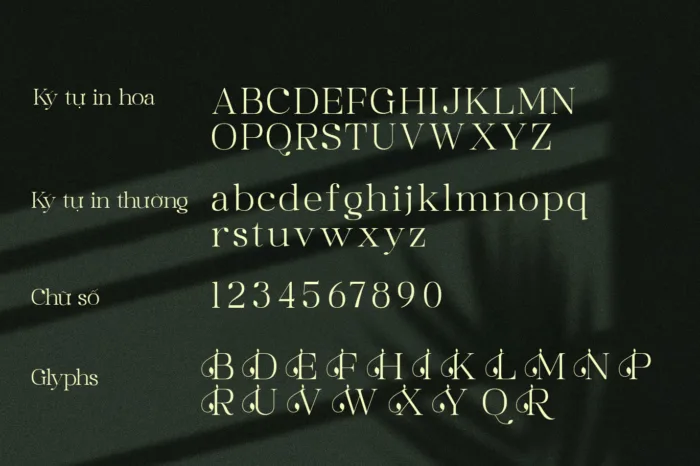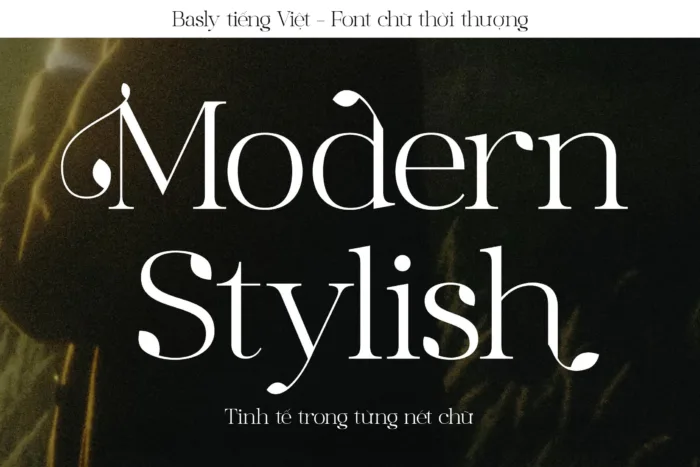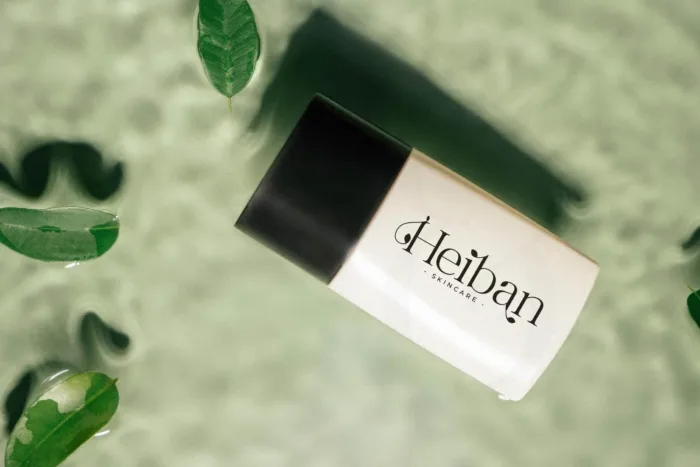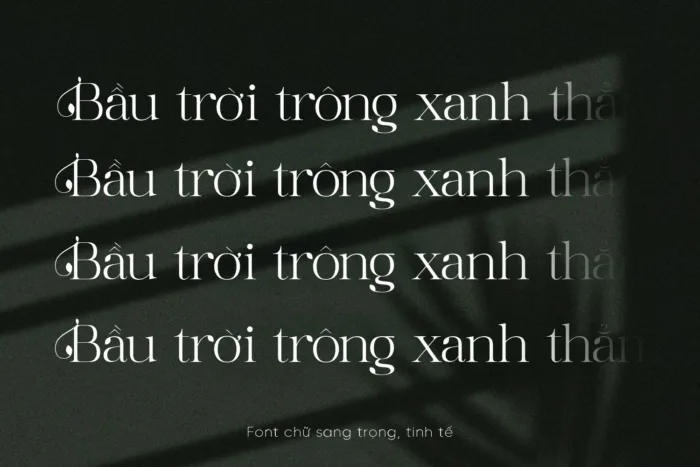
DVN Basly tiếng Việt – Font chữ Thanh lịch & Thời thượng cho thiết kế cao cấp
DVN Basly là một typeface serif Việt hóa mang phong cách hiện đại pha chút cổ điển, với những đường nét uyển chuyển và điểm nhấn tinh tế ở các ký tự. Font mang đến sự sang trọng, thích hợp cho các dự án branding, thời trang, mỹ phẩm, bìa sách hay tạp chí.
Điểm nổi bật của DVN Basly là sự kết hợp giữa các nét thanh mảnh và chi tiết uốn lượn độc đáo, tạo nên cảm giác vừa mạnh mẽ vừa mềm mại. Bộ font hỗ trợ đầy đủ tiếng Việt, đảm bảo tính ứng dụng cao trong thiết kế đồ họa và truyền thông.